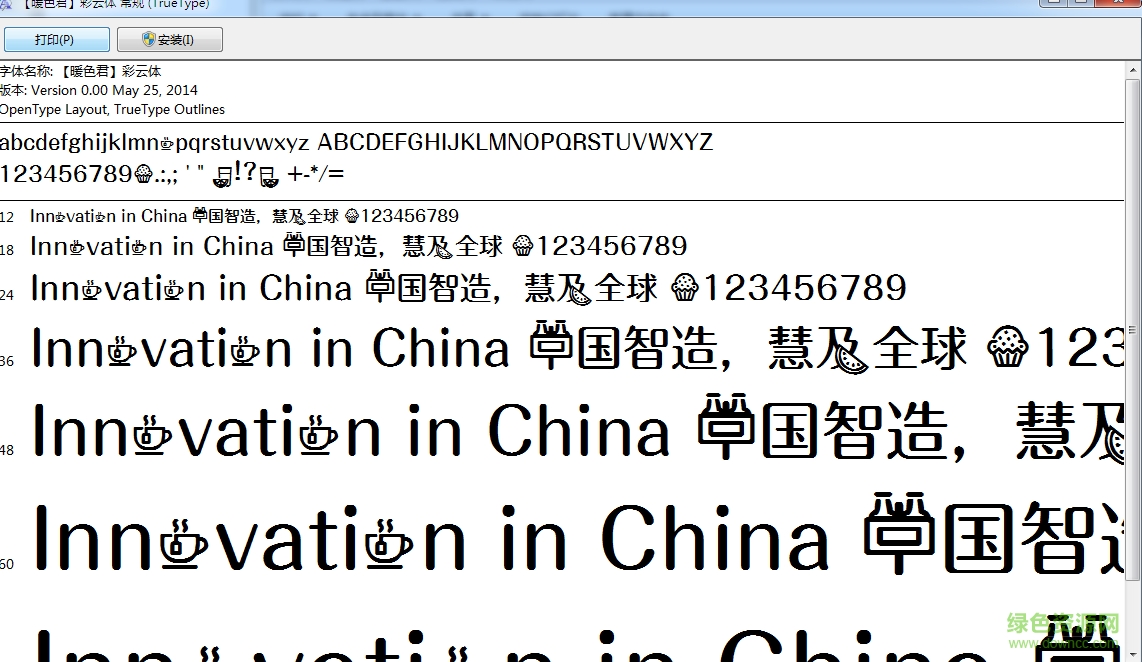
暖色君彩云體
暖色君彩云體字體是一款非常有特色的字體,字體中加入了水果、冰淇淋等特色,看上去非常的萌,用來制作各種各種可愛的設(shè)計再適合不過了,喜歡的朋友歡迎來了綠色資源網(wǎng)下載!
字體簡介
暖色君彩云體是一款萌萌噠字體,字形粗黑可愛,筆畫清新灑脫,整體散漫隨意,識別度非常高,字體糅合了小動物頭像、愛心、圓圈、冰淇淋等各種可愛的元素,非常適合用來制作個性簽名!
暖色君彩云體字體